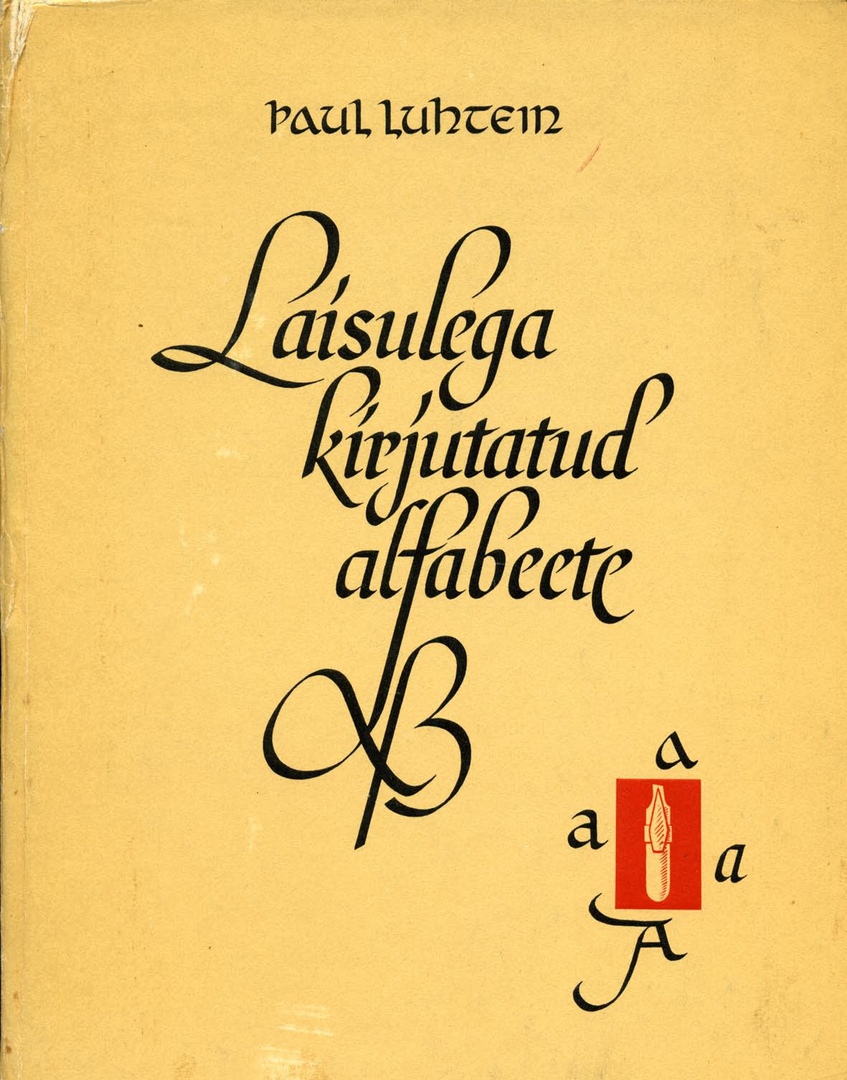
«Шрифты написанные ширококонечным пером», Пауль Лухтейн
Хороший шрифт логично построен, в нем каждая буква соответствует в своем рисунке рядом стоящим буквам. У каждого хорошего шрифта есть свои характерные признаки, которые формируют конкретный алфавит. Красивый шрифт должен быть написан свободно, плавно и непринужденно, решен смело и своеобразно, в нем должна быть подчеркнута хорошая форма и хорошее расчленение. Исходя из предыдущих принципов и анализируя каждый предшествующий образец шрифта, создадим основу для результативной работы.